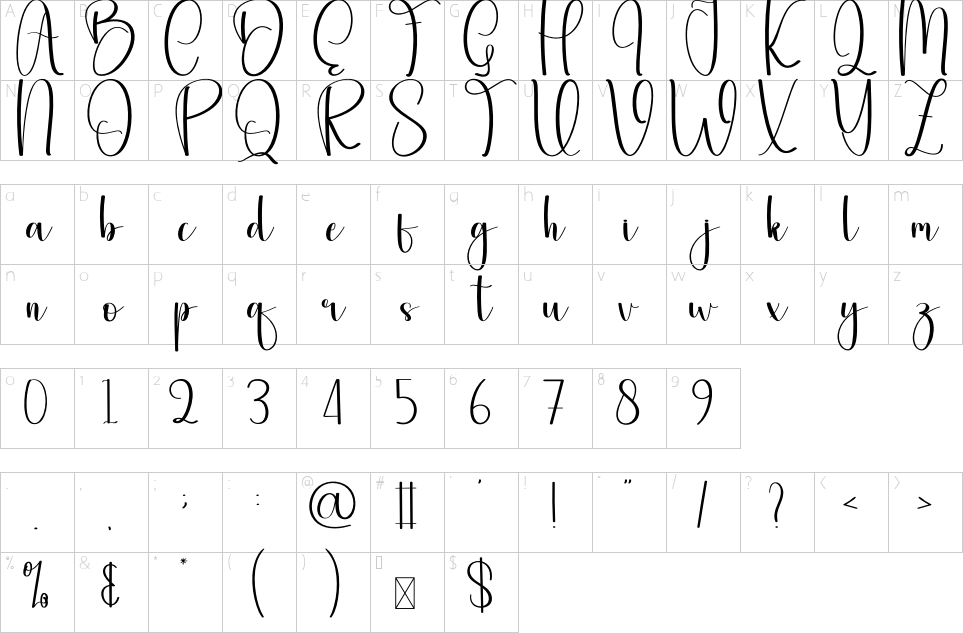
Descubra a Party Vintage Font, uma fonte gratuita e vintage perfeita para personalizar seu design de forma única. Desenhada pelo talentoso designer William Jhordy, essa font oferece uma experiência de estilo clássico para seus projetos. Com seus traços finos e detalhes elegantes, Party Vintage é perfeito para criar designs que transmitam nostalgia e elegância. Seja para uma festa vintage, um site personalizado ou até mesmo um documento de trabalho, essa fonte adicionará um toque autêntico e sofisticado a qualquer projeto. Disponível tanto para sistemas Windows quanto para Mac, a Party Vintage Font é um download atraente para quem busca uma fonte única e gratuita. Seja o primeiro a desfrutar dessa elegante opção gráfica.